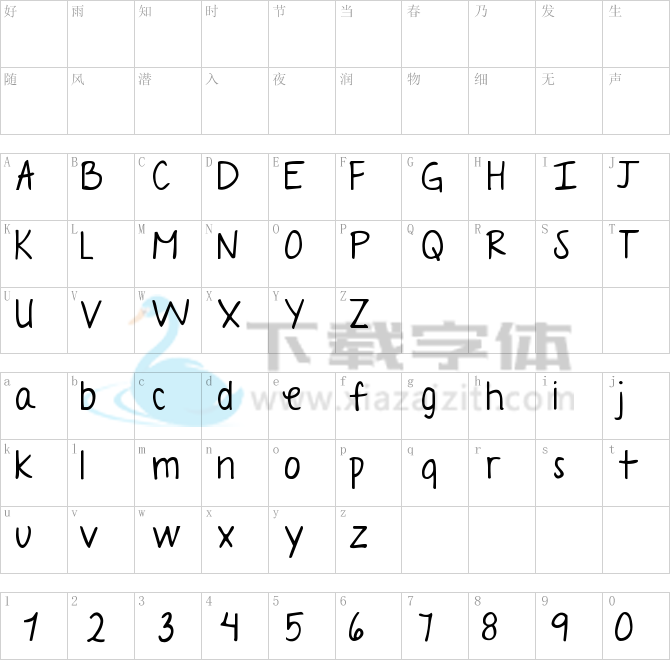
A Year Without Rain.ttf字体下载,这款字体结构工整、笔画清晰,兼顾美观与易读性,适用于标题、正文、海报、包装、LOGO 等多种场景。字形优雅稳定,风格百搭耐看,适配日常排版与创意设计,让文字呈现更舒适、更具质感。A Year Without Rain.ttf字体下载一笔一画,皆是细节,以均衡的比例、流畅的线条打造舒适视觉体验,字形端正大气,风格简约现代。无论是商业设计、品牌宣传还是日常排版,都能轻松驾驭,让文字更有格调与力量。A Year Without Rain.ttf字体下载字体下载。
• 字体名称:A Year Without Rain
• 字体标识 ID:KimberlyGeswein: A Year Without Rain: 2012
• 字体全名:A Year Without Rain